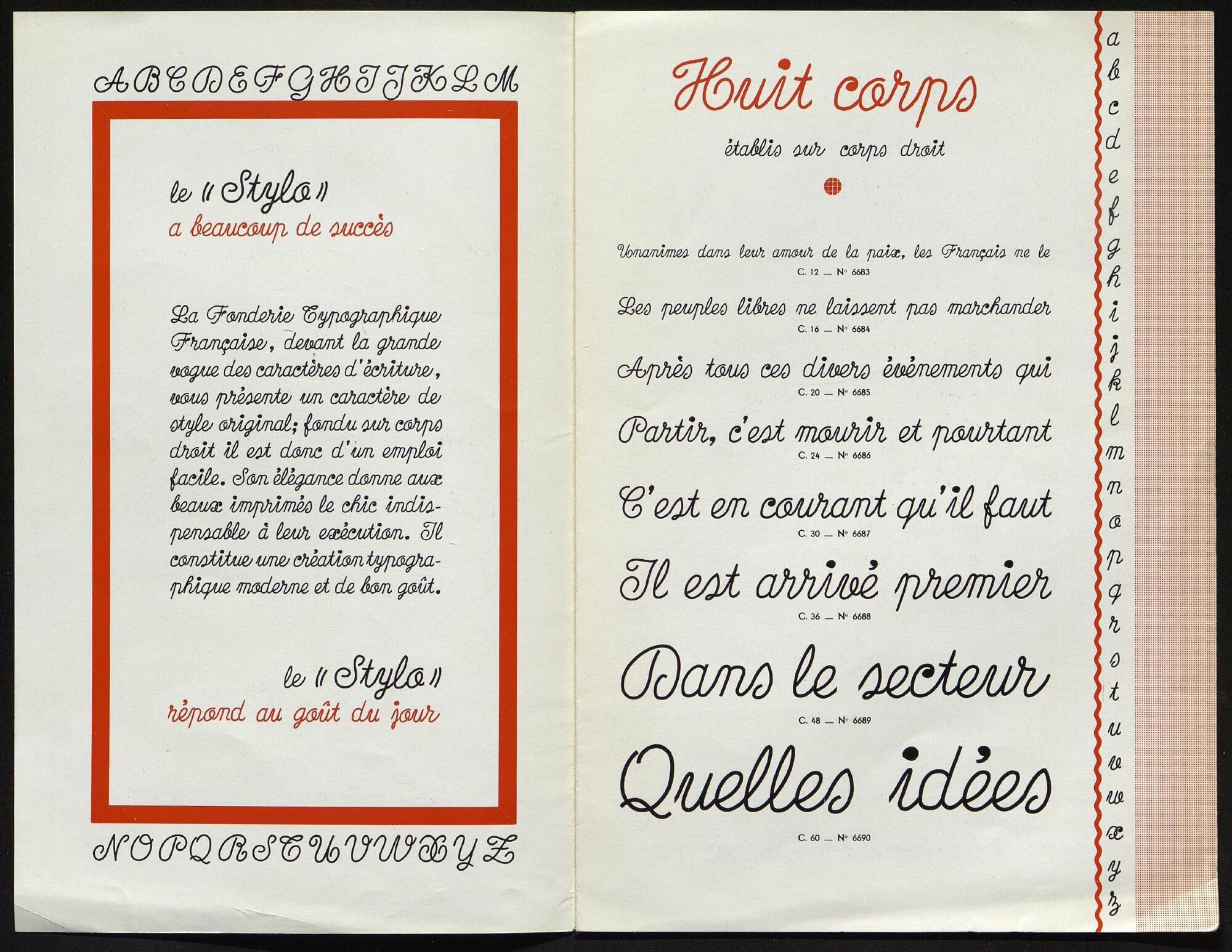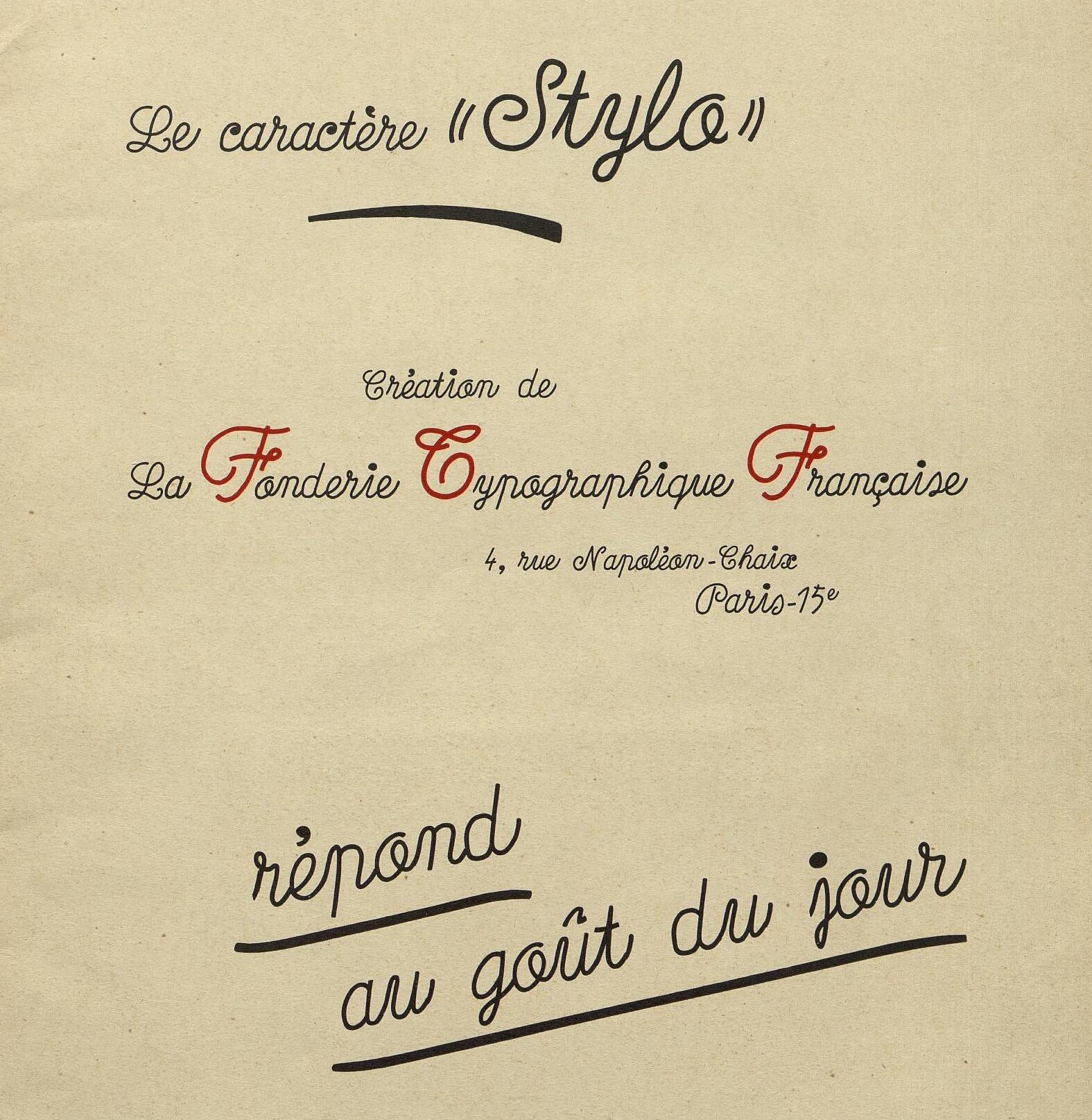
Die Stylo ist eine verbundene Werbeschreibschrift des französischen Herstellers Fonderie Typographique Française und erschien in den 1930er-Jahren.
Digitalisierungen sind nicht bekannt.